如果您是图形设计师,那么选择要使用的字体可能会令人生畏。但是,我们在这里为您提供帮助,这些免费字体包可在一处编译数百种奇妙的字体。这意味着您可以轻松找到适合自己需求的东西。
1。 Typewolf Google字体集合
Google字体是嵌入式Web字体最受欢迎的目录。许多设计师认为它是宝贵的资源。但是,注册表中大约有900种字体,尝试选择要下载的字体可能有些不知所措。
Typewolf每年都会精选40种最佳Google字体。此包中包含来自著名字体设计师的字体,这些字体具有不同的重量和样式。该网站还突出显示了哪种字体看起来像正文一样好。
2。 TheHungryJPEG免费字体包
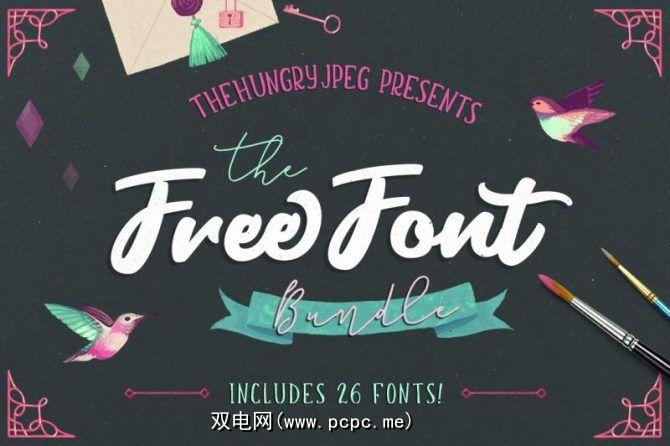
TheHungryJPEG是一个受欢迎的设计资源网站。它提供了高质量的字体,图形,图片,主题和模板。虽然大多数资源不是免费的,但TheHungryJPEG提供了26种字体,价值104美元,仅在社交媒体上发布费用。
此包中的大多数字体是显示字体和脚本字体。它们适用于大型印刷图形,在线帖子和邀请。例如,越前(Echizen)是一种手绘字体,在社交媒体布局上看起来非常出色。
3。 Ultimate Old-School PC字体
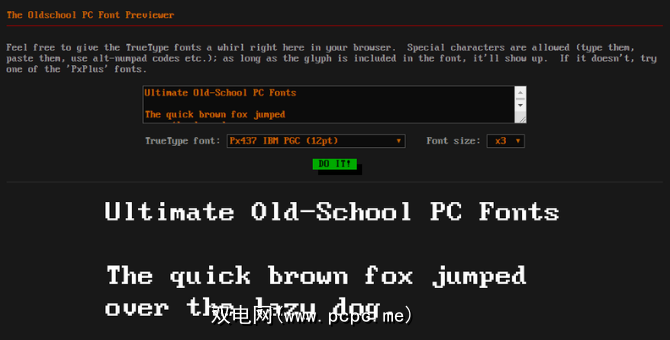
如果您的下一个设计项目具有复古美感,那么您将爱上Ultimate Old-School PC字体包。
这些字体很棒计算早期字体的复制品。那些在1980年代拥有计算机的人可以立即识别按照IBM PC,DOS设备和内置BIOS构图的字符。
此软件包中有81套字符。其中一些通过Unicode拥有多语言支持。所有这些文件只要是归设计师所有,都可以免费用于个人和商业用途。
4。 DreamBundles Type Lovers捆绑包
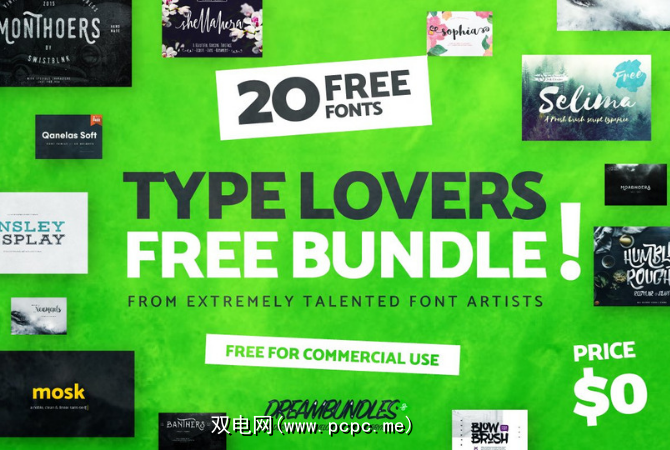
Type Lovers Bundle是Dreambundles免费提供的20种时尚字体的汇编,该服务提供了捆绑的设计资源。所有这些字体的样式都不同,并且都可以免费商业使用。
此产品包中的字体适合各种情况。 Mosk是干净的无衬线字体,具有9个权重,而Selima Script是一种画笔脚本,可以在自然照片和风景之上很好地工作。
各种各样的艺术家和设计师为此做出了贡献。如果您喜欢这种包装中的特定字体,则可以访问设计师的网站来进行他们所做的其他工作。
5。坚不可摧的字体
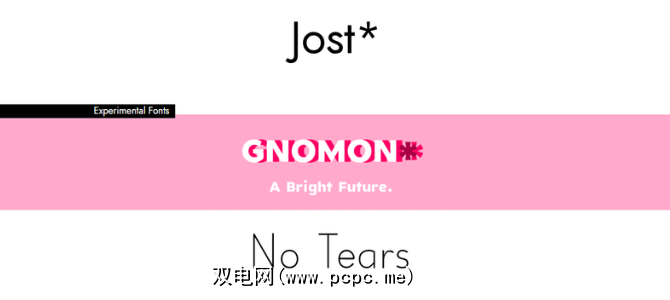
在浏览坚不可摧的字体时,您会很快注意到大多数字体都带有星号。这些星号是字体名称的一部分。开发此铸造厂的艺术家Owen Earl使用它们作为脱颖而出的方法。
Indestructible Type是一系列独特的原型字体的所在地,这些字体都具有广泛的通用性。 Gnomon *是用于大规模设计的粗体字体。 Bodoni *是一种衬线,意在所有大小均可读。虽然No Tears是Comic Sans的衍生版本,但已清理完毕。
6。伊吉诺·马里尼(Igino Marini)的Fell Types复兴
1668年,来自牛津的主教John Fell博士开发了一套他想用于基督教出版物和文字的类型。牛津大学于1686年去世后,保存了他的字体,并开始以自己的风格出版。
2000年代,意大利工程师Igino Marini开始将Fell字体重新创建为现代字体文件。这里的13种醒目的衬线字体是其类型的准确复兴。所有这些文件都放在一个zip文件中。只要您将它们归功于设计师,它们都是免费的。
并不是每个设计师都能说他们使用的是1600年代开发的字体,但是现在您可以了。
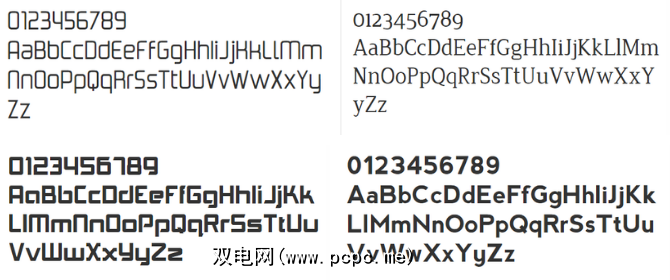
“二十个十岁"是英国设计师Ed Merritt的一组版式项目。在他的网站上,您可以找到他的9种字母数字字体和1种标志性字体。
他的字体种类繁多,从可立即发布的衬线(如Jura)到有趣的,块状的显示屏(如Tödi)。他的字体下载量超过150万。它们都是在开放字体许可下获得许可的,因此它们对所有类型的使用都是免费的。
8。 Linux Libertine字体
只有两种字体,这是此列表中最小的一组。但是,两者都非常有用。
Linux Libertine字体旨在替代标准Windows和Mac字体。因此,它们针对UI / UX设计,文字处理和文本发布进行了优化。
Libertine和Biolinum具有简洁的数字,大写字母和真实分数。这些文件可在tgz归档文件中找到,如果需要了解更多信息,请按以下步骤从常见归档文件中提取文件。
9。 Adobe Collections
Adobe Collections是从其字体库中提取的30种免费字体包。每个包装均由设计专业人士针对特定用途进行策划。有用于户外布局,创建路牌和行动主义材料的集合。
10。 Velvetyne铸造厂
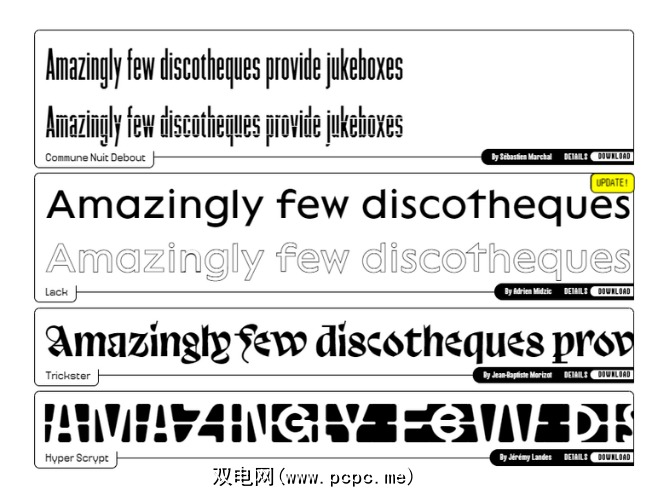
Velvetyne字体铸造厂或VTF是您在线上看到的最引人注目的和不寻常的收藏之一。您会发现各种各样的字体,从诸如Blocus的哥特式脚本到诸如Terminal Grotesque的朋克像素字体。